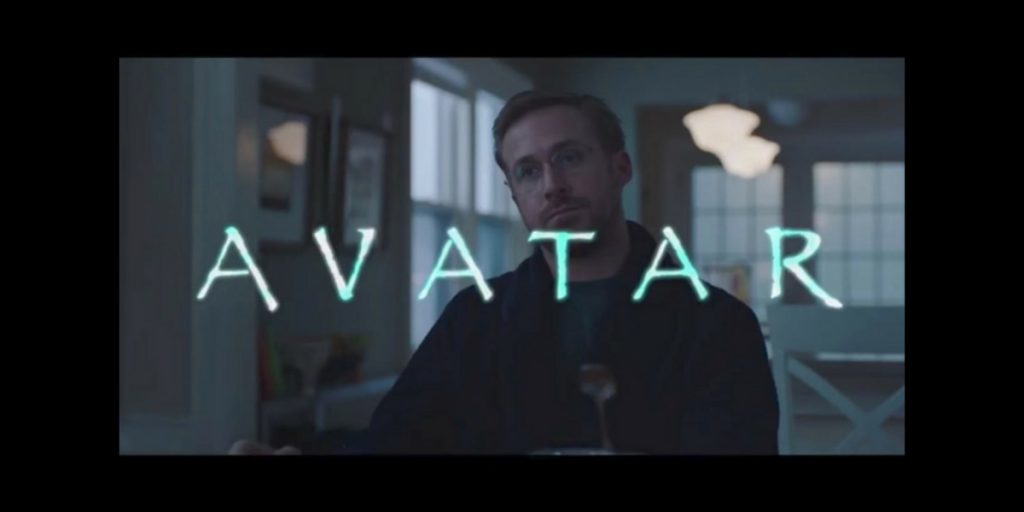
Parodie: Ryan Gosling verzweifelt an der Schriftart “Papyrus“
“Avatar – Aufbruch nach Pandora“ ist James Camerons erfolgreichster Kinofilm. Der Science-Fiction-Streifen spielte über 2,78 Milliarden US-Dollar ein. Zu beanstanden gibt es aus kommerzieller Sicht also nichts. Aus ästhetischer Perspektive wiederum wurde der Film, was die Auswahl der Schriftart beim Titel betrifft, durchaus kontrovers diskutiert. Die Entscheidung fiel damals auf “Papyrus“ und nicht wenige Designer fragten sich: Wtf. Am vergangen Wochenende wurde bei “Saturday Night Life“ diese alte Wunde wieder einmal aufgerissen, indem Ryan Gosling in einer Parodie einen verzweifelten Designer spielt, der einfach nicht darauf klarkommt, dass sich Cameron damals für “Papyrus“ entschied. Designer Problems, aber: Ein erstklassiger Sketch mit einem fantastischen Ryan Gosling.